Hat Gutefrage sein Font verändert?
Auf der App sieht es irgendwie anders aus
Also irgendwie kleiner
Ich persönlich finde die Schriftart nicht schön
Ja, das ist mir hier auf der Website aufgefallen. Esist kleiner und sogar eine andere Schriftart glaube ich.
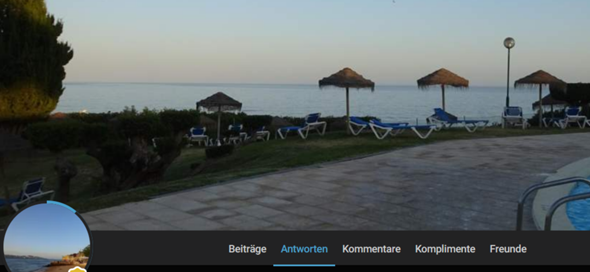
ja die untermenüs für "alle fragen" usw haben einen shadowdrop update bekommen
Ja, GF hat sein Front verändert.
nicht dass ich wüsste
Ja, beim Profil ist diese eine Schrift kleiner geworden. Ich fand's vorher besser.😐
Ist aber nicht schöner, eher das Gegenteil oder